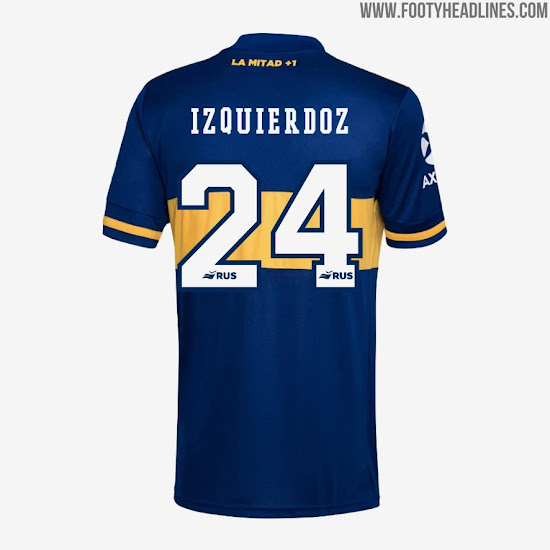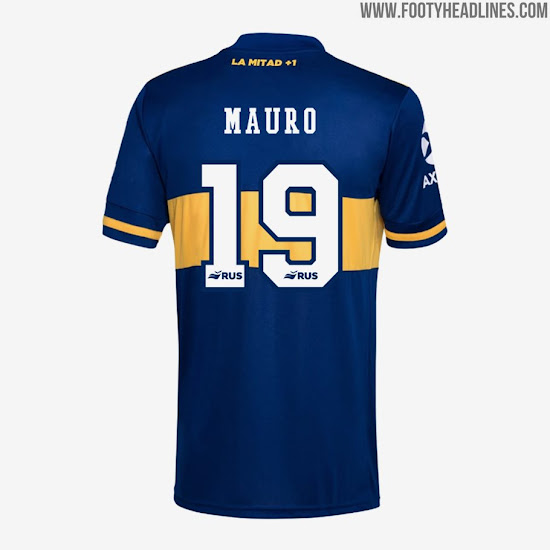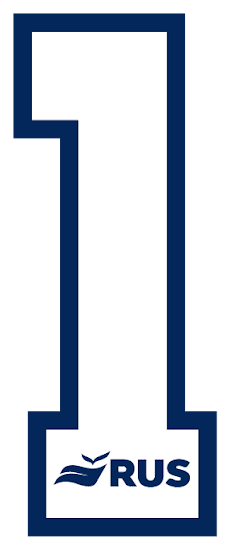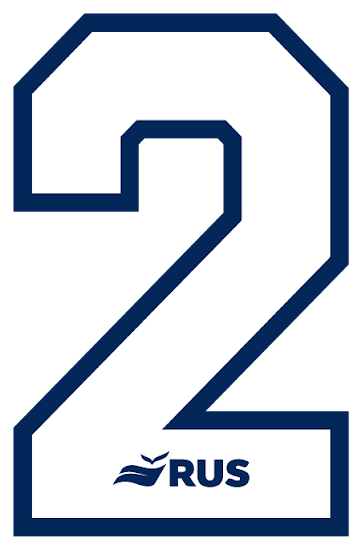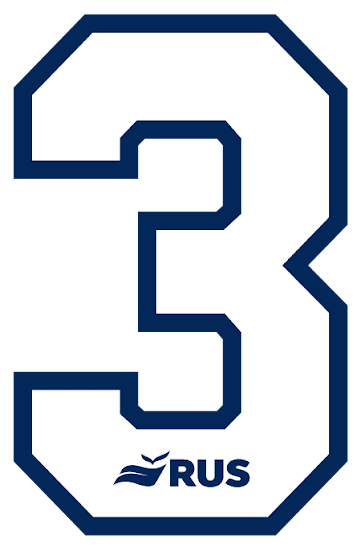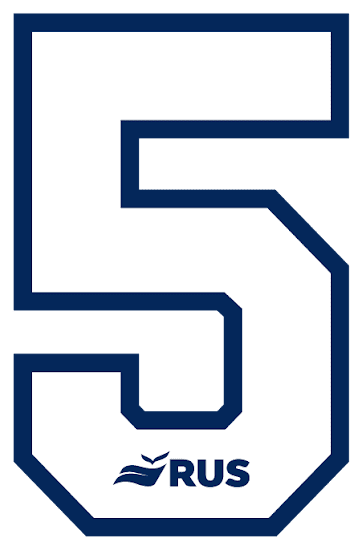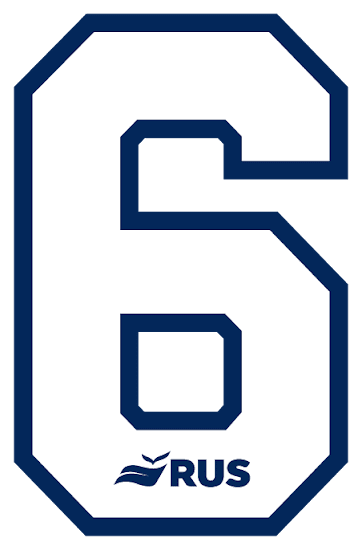
Adidas Boca Juniors 2020 Trikot-Schriftart veröffentlicht
Adidas hat für die neuen Boca Juniors 2020 Trikots eine maßgeschneiderte Schriftart entworfen. Schauen wir uns die neue Boca Juniors 2020 Trikot-Schriftart genauer an.
Adidas Boca Juniors 2020 Trikot-Schriftart
Die neue Adidas Boca Juniors 2020 Trikot-Schriftart ist sehr klassisch - die Schrift ist inspiriert von den Schriftarten der 1970er und 1980er Jahre, als Adidas der erste Ausrüster der Boca Juniors war.
Die Nummern auf dem Trikot sind weiß mit einem marineblauen Rand, während die Nummern auf dem Auswärtstrikot blau mit einem gelben Rand sind.
Im Inneren jeder Nummer befindet sich das Logo des Boca Juniors Sponsors RUS (Rio Uruguay Seguros), einer Versicherungsgesellschaft.